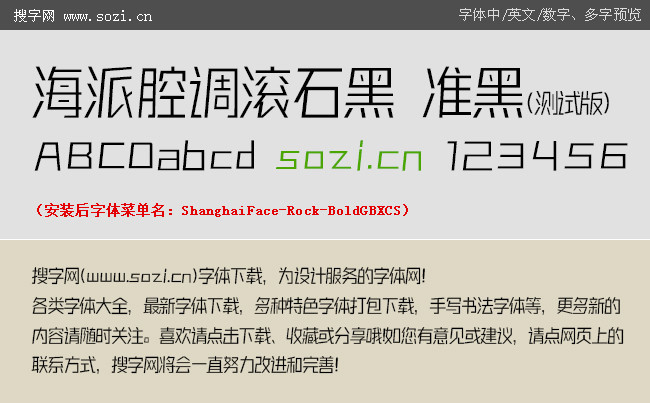
海派腔調(diào)滾石黑-準(zhǔn)黑(測(cè)試版)
搜字網(wǎng)提供一款海派腔調(diào)滾石黑-準(zhǔn)黑(測(cè)試版)中文字體下載海派腔調(diào)滾石黑是一款十分漂亮的藝術(shù)字體,字體略微傾斜,清晰、醒目,整體美觀大氣,適合用于報(bào)刊標(biāo)頭設(shè)計(jì),包裝設(shè)計(jì),海報(bào)設(shè)計(jì)等廣告應(yīng)用。(此款為個(gè)人非商用版,如需商用請(qǐng)聯(lián)系銳字工房購(gòu)買)